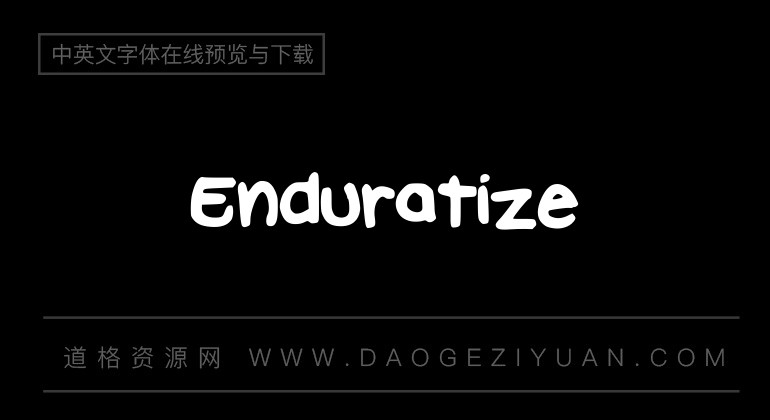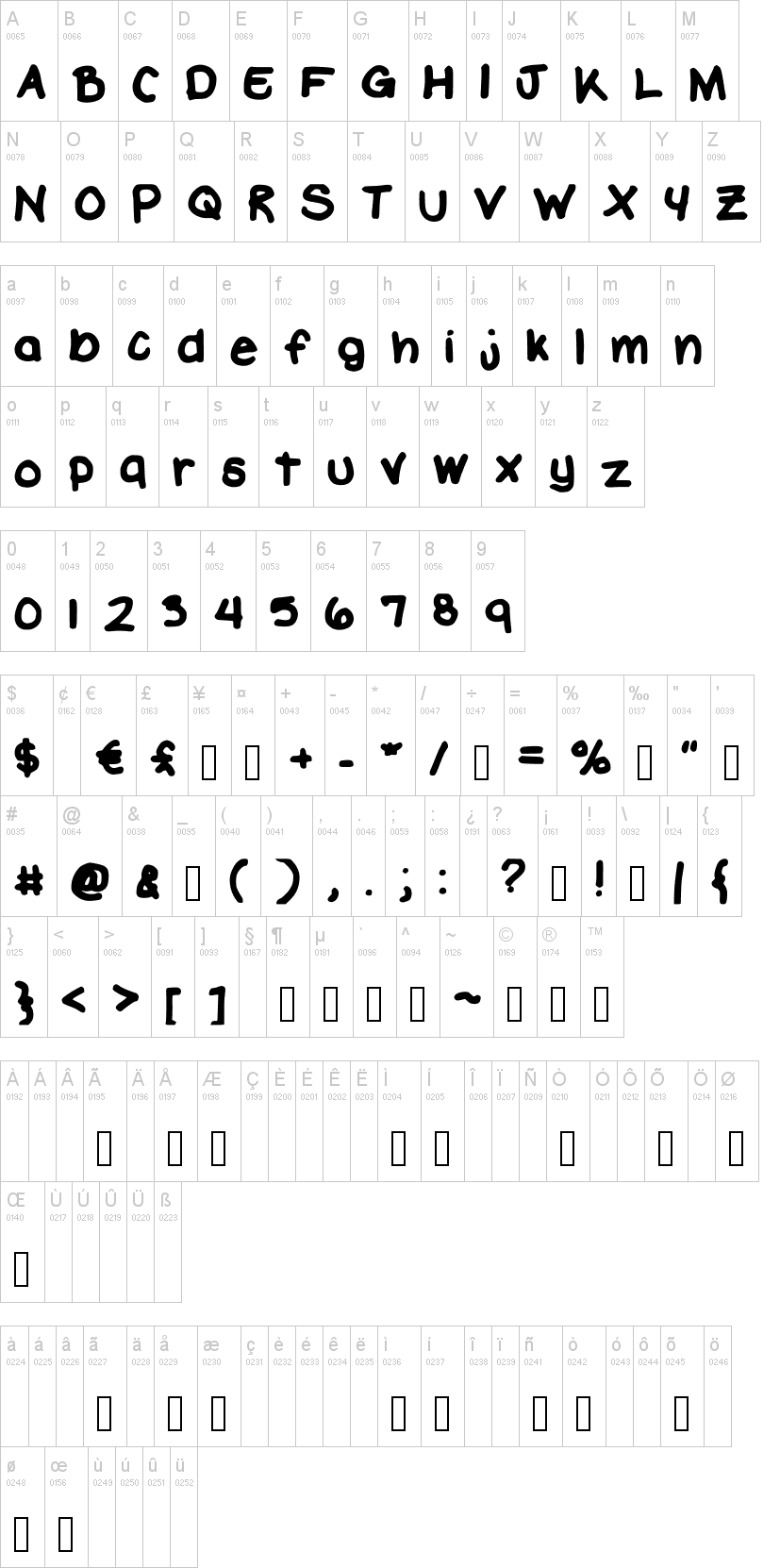
Enduratize
Enduratize 是一款由 Fontfabric 公司设计的现代字体。它采用了极其优雅的设计风格,具有流畅的线条,拥有清晰的细节,并且配有多种字重,可以满足不同的需求。它的字形可以支持多种语言,包括英语、拉丁语、希腊语和俄语等,可以满足您的多种设计需求。Enduratize 字体的设计风格精致而不失灵动,可以用于创建各种类型的印刷品、网页设计、标志设计和排版等。
Enduratize是一款非常不错的手写艺术字体,具有很好的视觉感,适合于文化类的宣传设计、商业类品牌的广告和产品包装设计以及个性化文字排版等较多场景。